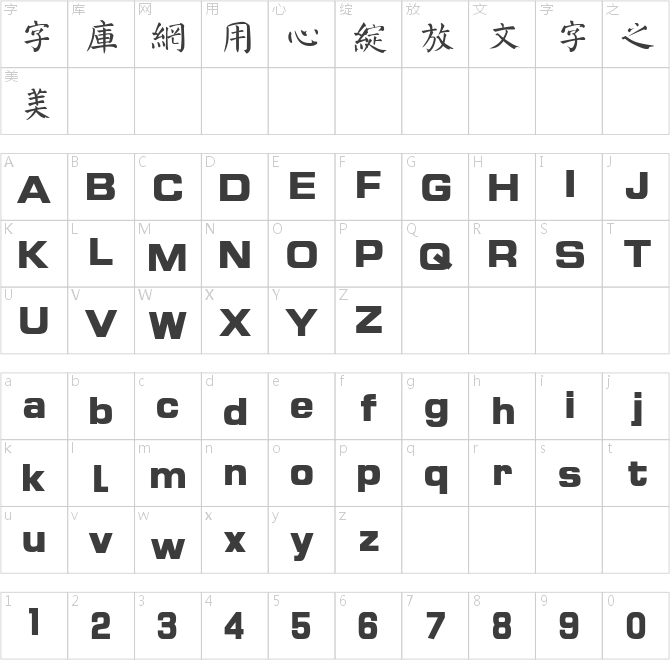
麻姑山顏楷 詳情頁
字體名稱: 麻姑山顏楷
作者版權: 字悅字庫
麻姑山顏楷
麻姑山顏楷字體下載楷書復刻字體麻姑山顏楷
麻姑山顏楷字體楷書復刻字體麻姑山顏楷字庫是一款讓人賞心悅目、百看不厭的中文字體,適合各類廣告和產品包裝設計應用,字體大小8.17MB,格式為ttf字體,上傳用戶是鯨魚只會打狙,作者/版權方為字悅字庫